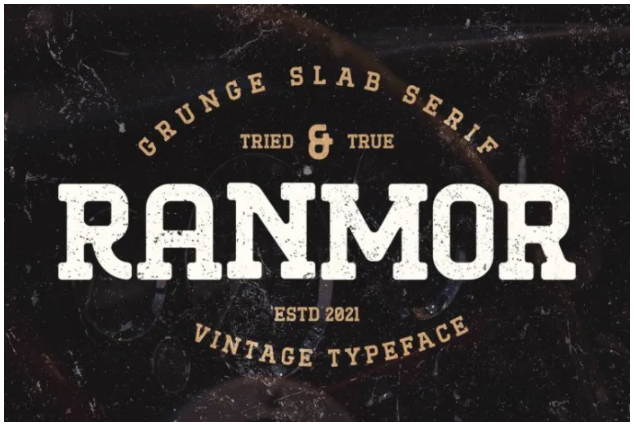
[Fontbundles] Ranmor Font (2021)
Ranmor - это винтажный шрифт с засечками. Вдохновленный винтажными логотипами и дизайном, Ranmor становится более сильным шрифтом благодаря добавлению гранжа и чернильного эффекта на формах букв. Этот шрифт идеально подходит для винтажных или олдскульных тем.
Ranmor олицетворяет силу, уверенность и эстетику старой школы. Вы можете использовать этот шрифт для различных целей, таких как винтажный логотип, кружка, вышивка, принты, дисплей, короткий текст, упаковка, открытки, эмблема, вывеска и многое другое! Шрифт оснащен специальными символами, чтобы сделать ваш дизайн более мощным.